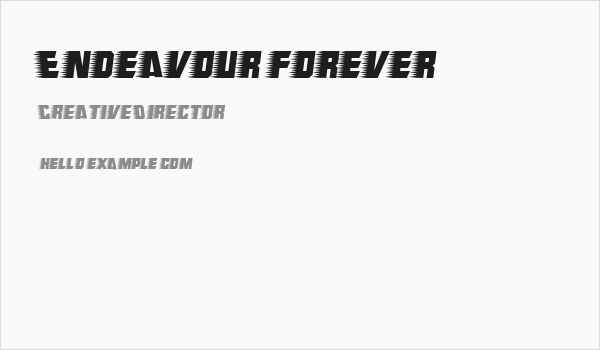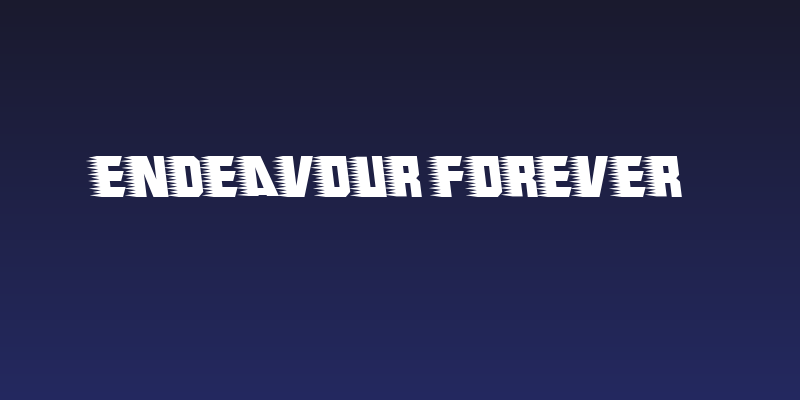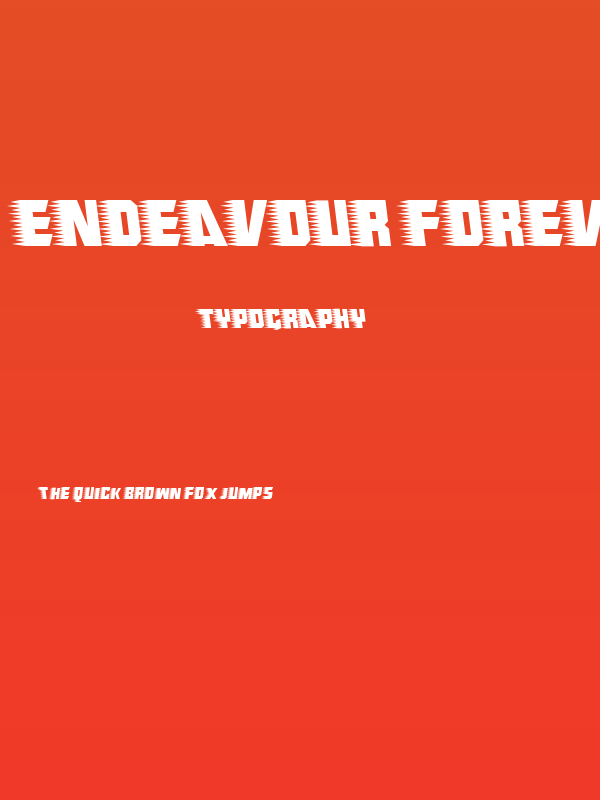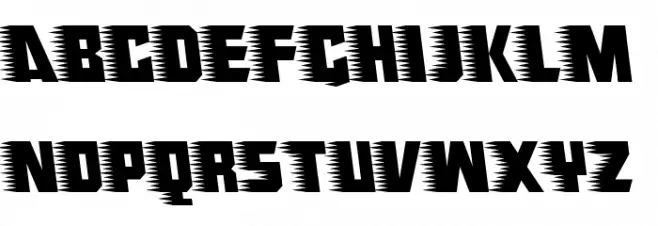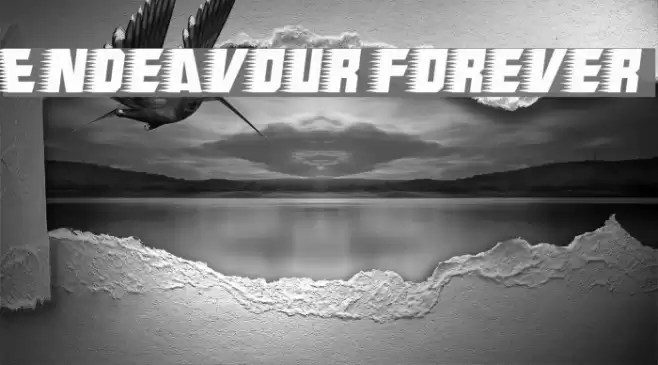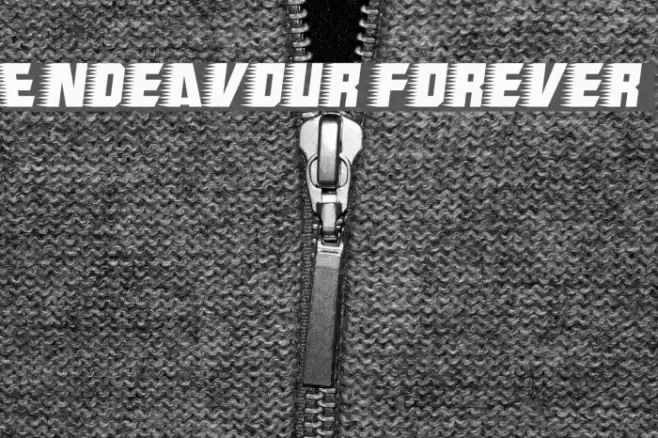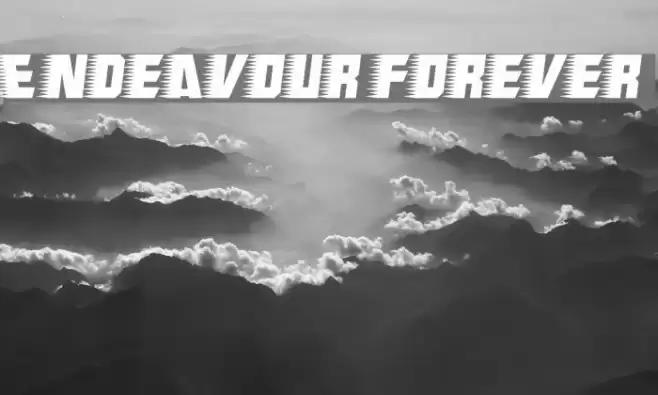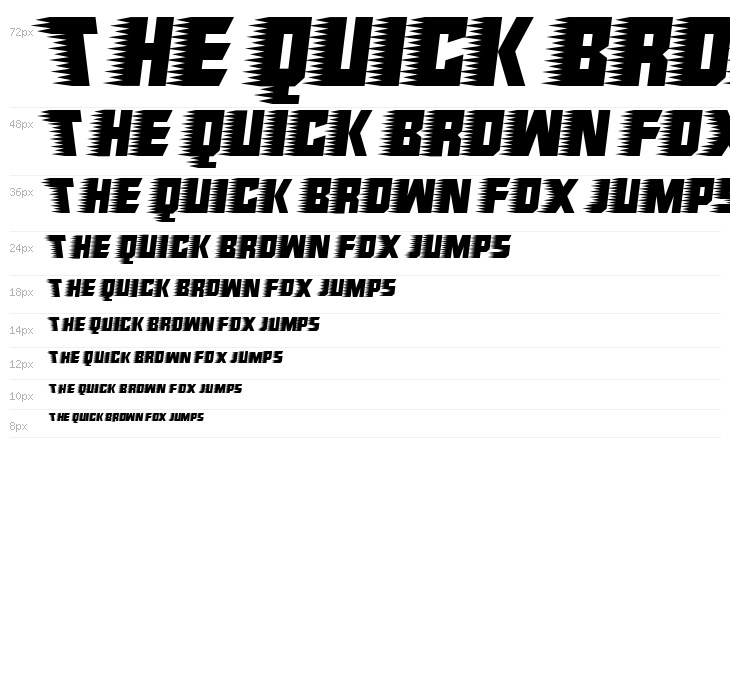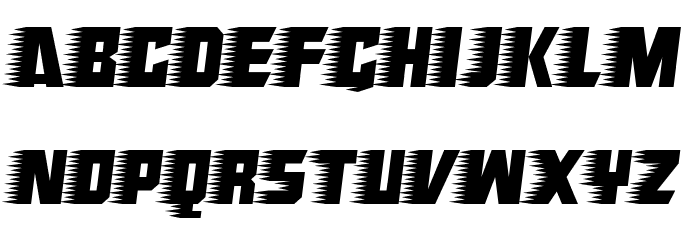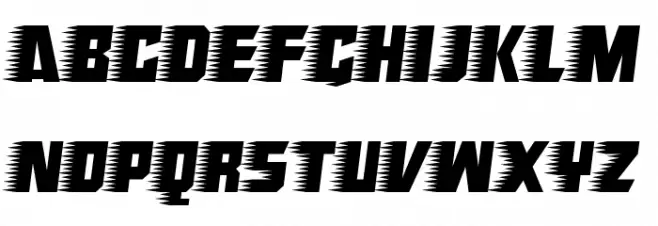
Endeavour forever Font
✎ Decorative
| कंट्रास्ट | High |
| उपयोग का मामला | Headlines, Logos |
| सुझाए गए प्रोजेक्ट | Perfect for sports branding, action movie posters, dynamic event flyers, and any project needing a bold statement. |